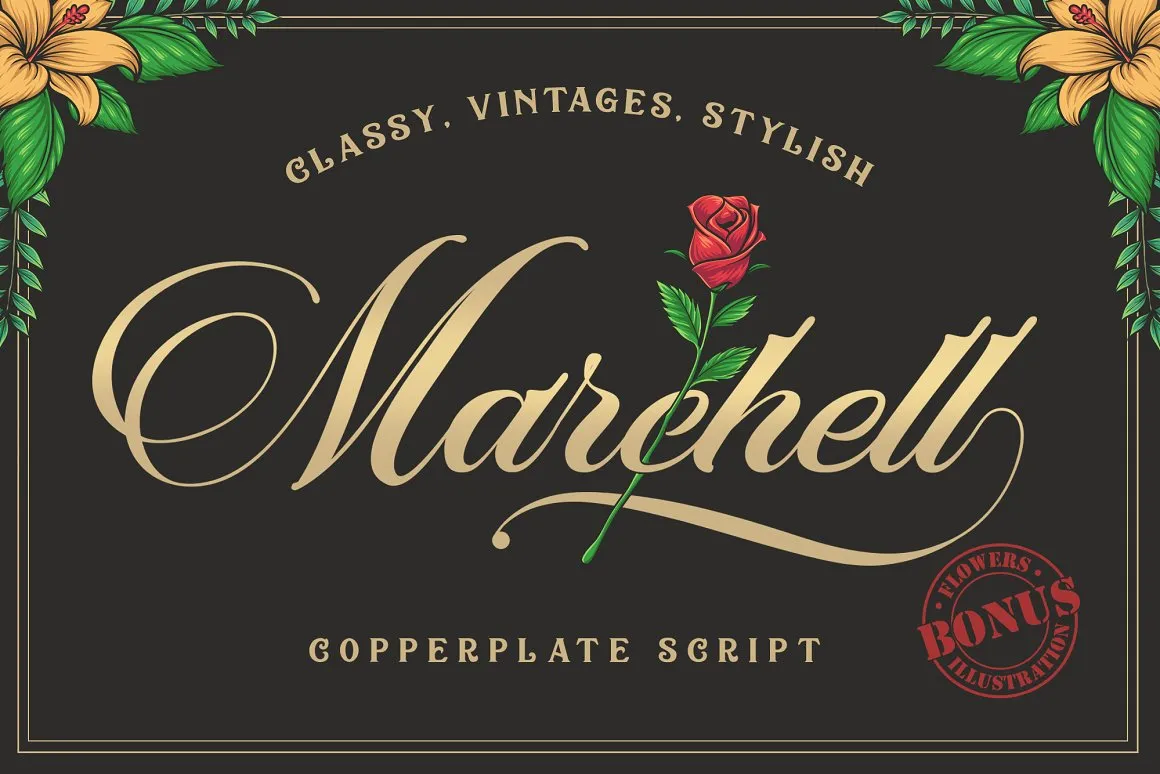
A Marchell Script Font é uma nova aquisição para qualquer designer que busque agregar um toque especial às suas criações digitais. Ela surge do mesmo estúdio que criou o famoso Copperplate, Blankids Studio, e traz uma experiência inovadora em design de fontes script. A Marchell não apenas revolucionaria sua versão visual, mas também transformaria seu trabalho em algo mais belo e interessante. Desenvolvida pelo designer Hamilton, a Marchell oferece um estilo que mistura clássico com modernidade, trazendo à tona elementos vintage e retro. Seu design elegante e luxuoso continua sendo geópsita aos dias atuais sem perder sua essência original. Perfeita tanto para identidades de marca como blogs e invitations para casamentos, a Marchell é uma opção excepcional que encaixa-se em diversos projetos digitais. Seja para t-shirts, posters ou até mesmo o design de logos, ela certamente dará um toque único à sua arte digital.